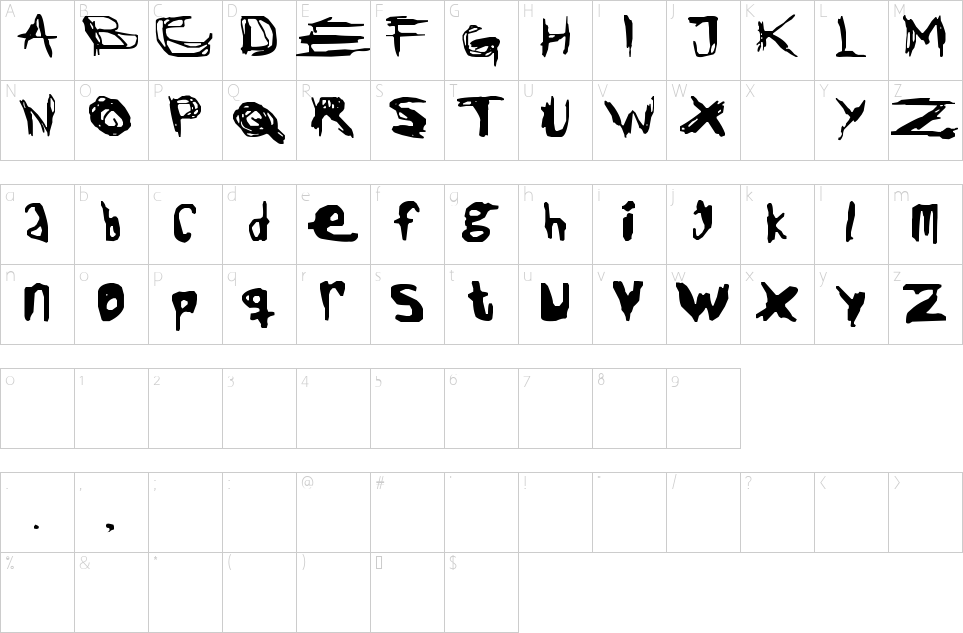
A Jack The Ripper Font é uma escolha perfeita para os amantes do gótico e das histórias perturbadoras, oferecendo uma feroz e elegante aparência que imediatamente remete às terríveis execuções ocorridas durante o período da Primeira Guerra Mundial em Londres. Esta fonte foi criada pelo designer anônimo Mr Fisk, e já foram baixadas 2.927 vezes. Com sua designação temática que faz uma conexão direta com a era sombria das Jack the Ripper assassinatos, a Jack The Ripper Font é ideal para aqueles buscando um estilo sinistro em seus projetos digitais. Seja você um escritor de histórias góticas ou um artista gráfico criativo procurando por uma maneira única de destacar seu trabalho, esta fonte adicionará um toque único e perturbador a qualquer projeto que você estiver trabalhando.